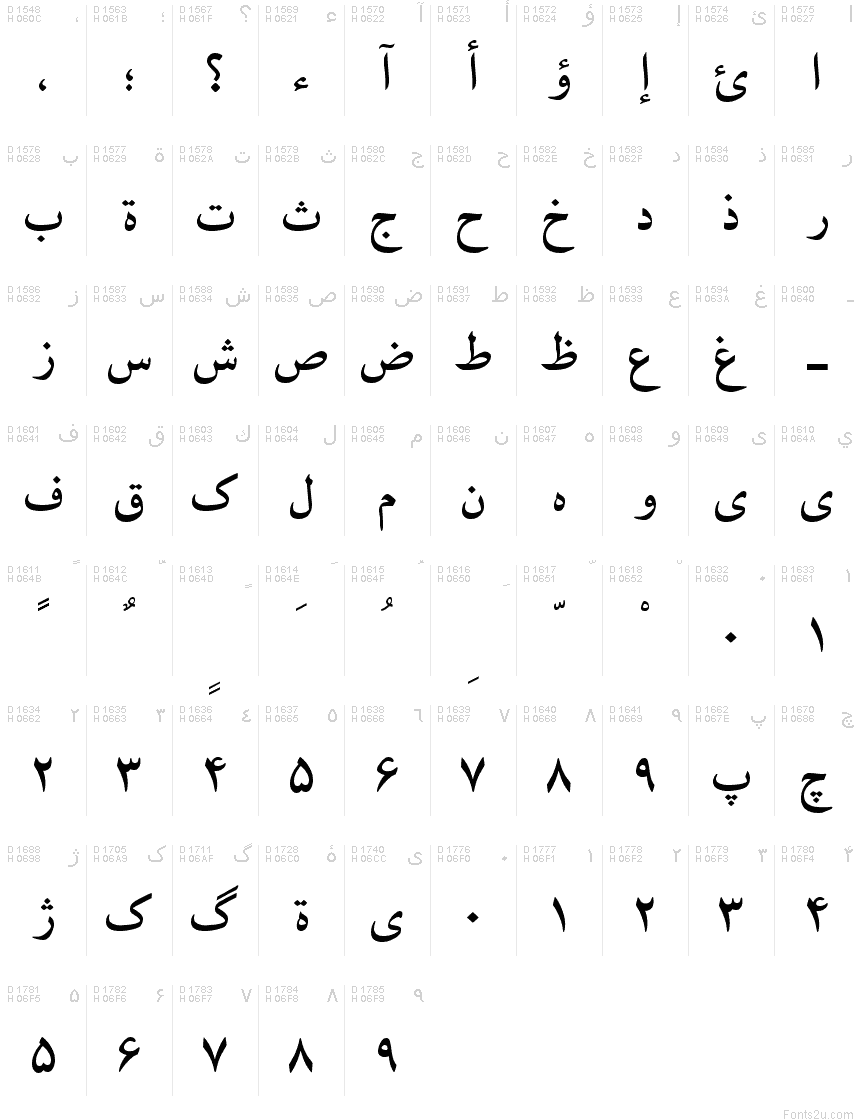
B Badr Bold autorstwa Borna Rayaneh to darmowy arabski font typu display o gęstym, kaligraficznym rytmie. Litery są kompaktowe i wyraziste, a zaokrąglone pociągnięcia oraz ostre łączenia nadają krojowi mocny charakter, stworzony do nagłówków, a nie do dłuższego tekstu.
Idealnie sprawdzi się na plakatach, okładkach książek, opakowaniach, w oprawie wydarzeń kulturalnych oraz w logotypach, które wymagają tradycyjnego, ale solidnego arabskiego sznytu. Jako darmowy krój świetnie nadaje się też do krótkich nagłówków redakcyjnych i tytułów, ponieważ pogrubione, połączone formy tworzą silny blok typograficzny nawet przy niewielkiej ilości tekstu.